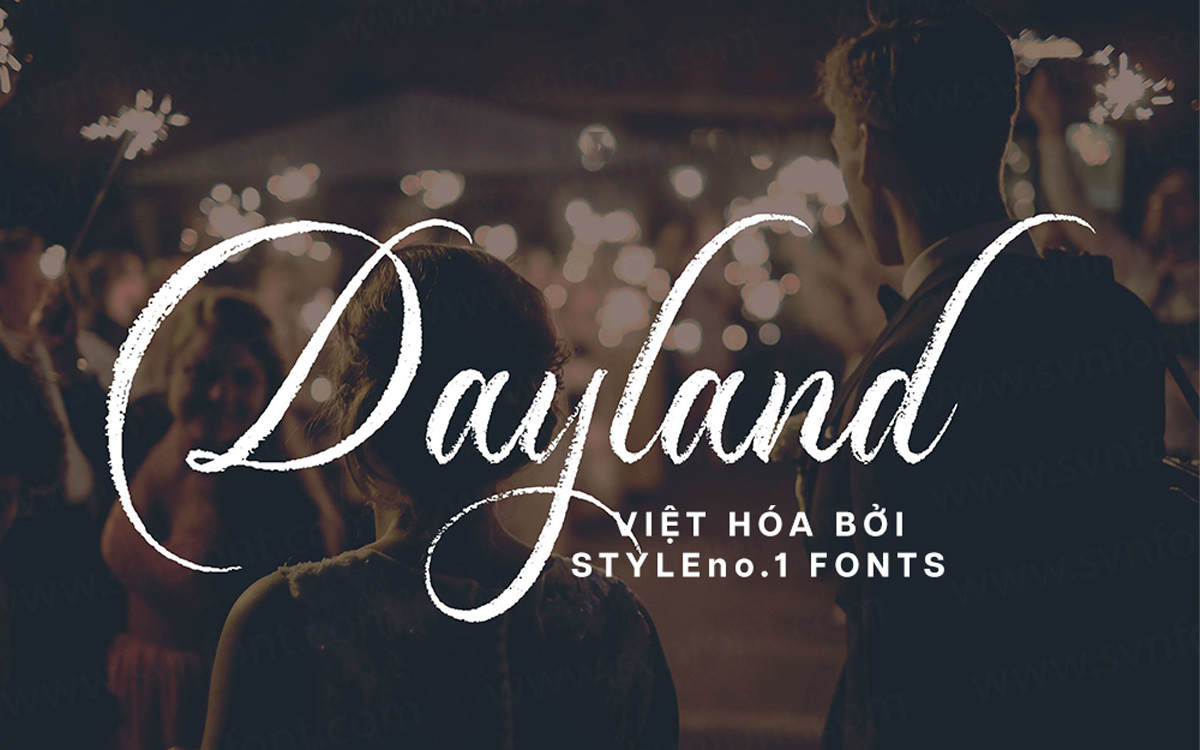
Font chữ viết tay mềm mại SVN-Dayland Việt Hoá là một trong những bộ font calligraphy nghệ thuật được cộng đồng thiết kế đồ họa săn đón nhờ vẻ đẹp thanh lịch, uyển chuyển và đầy cảm xúc. Với các đường nét uốn lượn tự nhiên mô phỏng nét bút thủ công tỉ mỉ, bộ font này mang đến sự lãng mạn và tinh tế cho mọi sản phẩm sáng tạo. Phiên bản Việt hoá hoàn chỉnh giúp người dùng tự do thể hiện các thông điệp bằng tiếng Việt một cách mượt mà mà không lo gặp sự cố lỗi font hay mất cân đối diacritics.
Sự xuất hiện của SVN-Dayland trong dự án thiết kế không chỉ đơn thuần là việc hiển thị văn bản, mà còn là một giải pháp nghệ thuật giúp nâng tầm giá trị thẩm mỹ cho toàn bộ tác phẩm. Nhờ sự kết hợp hài hòa giữa nét vẽ tay tự do và cấu trúc chữ hiện đại, font chữ này đáp ứng hoàn hảo yêu cầu khắt khe của các nhà thiết kế trong nhiều lĩnh vực từ truyền thống đến kỹ thuật số.
1. Đường Nét Calligraphy Mềm Mại, Tự Nhiên Và Giàu Cảm Xúc
Điểm đặc trưng nổi bật nhất của SVN-Dayland chính là hệ thống nét chữ uốn lượn vô cùng mềm mại. Mỗi ký tự được tạo hình tỉ mỉ với độ đậm nhạt linh hoạt, mô phỏng chính xác từng lực nhấn của ngón tay khi đưa bút mực trên chất liệu giấy cao cấp. Nhịp điệu chữ (rhythm) và khoảng cách giữa các ký tự (kerning) được căn chỉnh chuẩn xác, giúp câu từ hiển thị liền mạch, tự nhiên như một bức thư tay nghệ thuật thực sự. Tính thẩm mỹ cao này giúp SVN-Dayland dễ dàng thu hút sự chú ý của người xem ngay từ cái nhìn đầu tiên.
2. Hỗ Trợ Tiếng Việt Đầy Đủ, Tối Ưu Dấu Thanh Chuẩn SEO & Typo
Phiên bản SVN-Dayland Việt Hoá được tinh chỉnh kỹ lưỡng để hỗ trợ toàn bộ hệ thống bảng mã tiếng Việt chuẩn. Các dấu thanh như dấu sắc, huyền, hỏi, ngã, nặng cũng như các dấu phụ (ă, ê, ô, ơ, ư, đ) đều được thiết kế lại nhằm đảm bảo sự tương thích tuyệt đối với độ nghiêng và cấu trúc ký tự gốc. Sự sắp xếp hợp lý giúp văn bản tiếng Việt hiển thị đẹp mắt, không bị đè dấu, lệch nét hay làm phá vỡ tổng thể mềm mại của dòng chữ, mang lại trải nghiệm thị giác trọn vẹn cho khách hàng.
3. Tích Hợp Hệ Thống Ký Tự Thay Thế (Alternate Glyphs) Và Swashes Phong Phú
Một tính năng mạnh mẽ khiến SVN-Dayland trở nên biệt lập so với các font chữ thông thường là sự tích hợp của OpenType Features. Font cung cấp hàng loạt ký tự thay thế (Alternate Characters), các nét nối đặc biệt (Ligatures) và các đường đuôi uốn lượn (Swashes) trang trí ở đầu hoặc cuối từ. Nhờ tính năng này, người thiết kế có thể dễ dàng biến tấu chữ cái thành những nét chữ ký cá nhân hóa độc đáo, tạo điểm nhấn ấn tượng cho logo, tiêu đề hoặc các đoạn quote mà không cần mất thời gian vẽ lại bằng tay.
4. Ứng Dụng Đa Dạng Trong Thiết Kế Thương Hiệu Và Sản Phẩm Truyền Thông
Nhờ vẻ đẹp thanh lịch và ngọt ngào, font chữ viết tay mềm mại SVN-Dayland Việt Hoá trở thành lựa chọn hàng đầu cho vô số dự án sáng tạo. Bạn có thể ứng dụng font chữ này một cách linh hoạt trong các hạng mục như:
- Thiết kế thiệp cưới & Sự kiện: Tạo nên những mẫu thiệp mời lãng mạn, sang trọng và đầy tính nghệ thuật.
- Nhận diện thương hiệu thời trang & Mỹ phẩm: Thiết kế logo, bao bì, nhãn mác sản phẩm mang phong cách nữ tính, cao cấp.
- Truyền thông Mạng xã hội: Sáng tạo các bài đăng quote, banner quảng cáo, poster sự kiện thu hút lượng tương tác lớn trên Facebook, Instagram.
- Ấn phẩm in ấn nghệ thuật: Trang trí bìa sách, tạp chí, menu nhà hàng, quán cà phê theo phong cách vintage hoặc bohemian.
Gợi Ý Phối Font (Font Pairing) Nghệ Thuật Với SVN-Dayland Việt Hoá
Để tối ưu hóa hiệu ứng thị giác cho tác phẩm thiết kế, việc phối hợp SVN-Dayland với các font chữ khác đòi hỏi sự tinh tế. Dưới đây là một số nguyên tắc phối font hiệu quả mà các chuyên gia thiết kế khuyên dùng:
- Kết hợp với Font Sans-Serif (Chữ không chân): Đặt SVN-Dayland làm tiêu đề chính kết hợp với các font chữ không chân hiện đại như Montserrat, Roboto, hoặc Open Sans làm phần nội dung. Sự tương phản giữa nét uốn lượn nghệ thuật và nét thẳng tối giản tạo nên sự cân bằng hoàn hảo.
- Kết hợp với Font Serif (Chữ có chân thanh lịch): Khi cần thể hiện nét cổ điển và quý phái, hãy kết hợp SVN-Dayland với các font như Playfair Display hoặc Cormorant Garamond. Bộ đôi này vô cùng phù hợp cho các ấn phẩm thời trang cao cấp và thiệp mời sự kiện xa xỉ.
- Tránh sử dụng quá nhiều font chữ viết tay cùng lúc: Chỉ nên dùng SVN-Dayland làm điểm nhấn cho các từ khóa quan trọng hoặc tiêu đề. Tránh dùng chung với một font script khác để tránh gây rối mắt và làm giảm tính dễ đọc của văn bản.